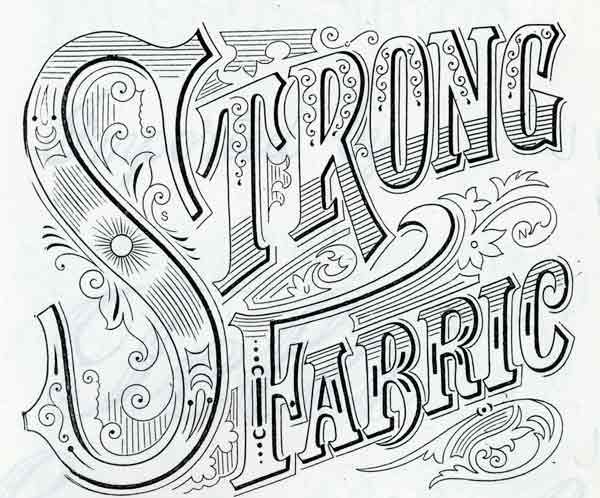
74. Шрифтовые формы XIX века
До конца XVIII века различия между книжными, рекламными и газетными шрифтами не существовало, употреблялся один и тот же шрифт, но разного размера. С активным развитием промышленности и торговли в XIX веке начали возникать новые стили шрифтов для газетных объявлений, рекламы и других акцидентных (т.е. выполняемых по случайным, разовым заказам) работ. Эти шрифты отличались от книжных особым, бросающимся в глаза рисунком. Эксперименты в области шрифтовой формы привели к возникновению новых видов шрифта.
К таким акцидентным шрифтам принадлежит появившийся в начале XIX в. египетский или брусковый шрифт.
Отличительным
признаком этого шрифта является
одинаковая толщина всех линий и засечек
букв. При этом пропорции и расположение
засечек такие же, как у антиквы. Существуют
разновидности египетского шрифта с
большим или меньшим различием в
насыщенности основного и дополнительного
штриха. Известнейшие из типографских
египетских шрифтов — Мемфис и Бетон
работы немецких шрифтовиков Рудольфа
Вольфа и Гейнриха Иоста.
Существует два подвида египетского шрифта.
Первый из них — это итальянский шрифт, весьма популярный в XIX в. Это узкий шрифт, по строению напоминающий рустику. Горизонтальные штрихи в несколько раз толще вертикальных.
Второй подвид египетского шрифта — это кларендон. Его признак — слегка округленные засечки и больший контраст между толщиной основного и дополнительного штриха.
В 1816 году появляется шрифт, на фоне многовекового господства антиквы выглядевший странно и даже смешно, за что и получил свое название — гротеск (от фр. смешной). Это шрифт с минимальным контрастом между основным и дополнительным штрихами и полным отсутствием засечек.
Гротески,
как и египетские шрифты, создавались в
качестве акцидентных и на большее не
претендовали. Однако в 1896 году берлинская
словолитня «Бертольд» выпустила
серию шрифтов, которые, несмотря на свое
название «Акцидент-гротеск», оказались
пригодными для набора текстов.
Акцидент-гротеску предстояло стать
прототипом новой шрифтовой эстетики.
Он появился незадолго до того, как
«новые типографы» назвали гротеск
«объективным и наднациональном шрифтом
современности». И действительно, именно
гротески обусловили облик типографики
XX в.
Кроме названых шрифтов в XIX в. на фоне общего упадка типографических традиций появляется огромное количество декоративных шрифтов, как правило — искаженных, противоестественных форм. Конструктивная неясность и декоративная перегруженность таких шрифтов формировала тенденцию к упадку художественного шрифта во второй половине XIX в., периоде, получившем название периода типографической эклектики.
времени сохранились тексты, напечатанные
на этом устройстве.[3]
Эпоха ренессанса не расширяла никогда первоначальной формы шрифта. Дидо, наоборот, выдвинул положение о серии шрифтов — узких, широких, жирных, тонких и т. д.
В XIX в. было создано огромное количество всевозможных шрифтов самых разнообразных рисунков. В Англии в начале столетия появляется характерная разновидность шрифта с чрезвычайно тонкими дополнительными штрихами и одновременно чрезвычайно жирными основными.
Это
так называемый жирный гротеск Торна
(1803 г.), за которым последовал в 1824 г. еще
более жирный шрифт (рис. 318). Не следует
путать этот шрифт с гротесковыми шрифтами
в современном смысле этого слова. В
настоящее время мы называем гротесками
шрифты типа древнего (рубленый,
рояль-гротеск и т.
д.).
Появление шрифта Торна вполне закономерно. Столь же закономерно появление его именно в Англии. До конца XVIII в. различия между книжными, газетными и рекламными шрифтами не существовало. И газета, и рекламные листки печатались одинаково простым шрифтом. С промышленным переворотом начал вырабатываться особый стиль оформления газет, реклам и акциденции, отличный от книжного. Этот особый стиль оформления требовал и особых, специфических шрифтов. |
Застрельщиком была Англия как страна с наиболее развитой промышленностью. Континентальная Европа покупала английские машины и копировала английские шрифты. Франция, Германия, Голландия, Испания выпустили ряд шрифтов. Появились жирные шрифты самых различных рисунков, соответствующих рисункам светлых шрифтов.
1. Stay Alive StayAlive